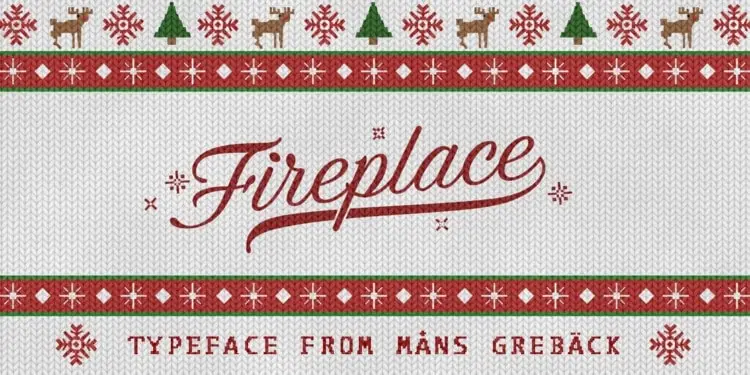
Fireplace Calligraphy Font – Download Grátis
Este Fireplace Calligraphy Font traz uma estética única com opções alternativas que permitem grande flexibilidade na sua criação. Desenhado pelo designer Mans Greback em 2020, esta tipografia script é perfeitamente apropriada para logotipos decorativos. Com um ar acolhedor e quente, ela remete ao espírito do Natal e da estação de inverno. O Fireplace Calligraphy Font surge como uma fonte vintage com velocidade, estilo e elegância. Uma característica interessante é sua atmosfera natalina e invernal, que o leva diretamente para a quente noite de Natal ou para as semanas frias do inverno. O design da fonte inspirou-se em letras esportivas vintage com um toque moderno de estilo único. Este Fireplace Calligraphy Font é perfeito para aqueles projetos que exigem um touch acolhedor e quente, criando um ambiente festivo durante a época natalina ou no inverno. Engloba uma vasta gama de opções de estilos e texturas, tornando-o versátil e adequado tanto para personalização de logotipos quanto para design de materiais de decoração natalinos.